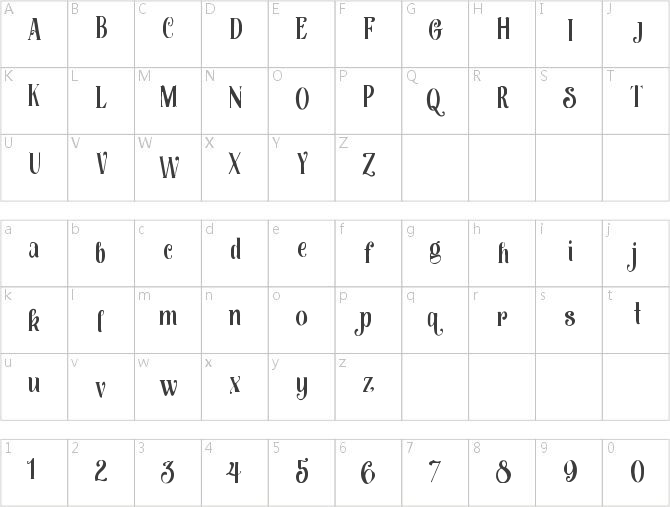
字體名稱: Afecta
Afecta Free Version
Afecta Free Version介紹
Afecta Free Version字體字庫是一款讓人賞心悅目、百看不厭的英文字體,適合各類廣告和產品包裝設計應用,字體大小0.09MB,格式為ttf字體,上傳用戶是Elieen,作者/版權方為未知